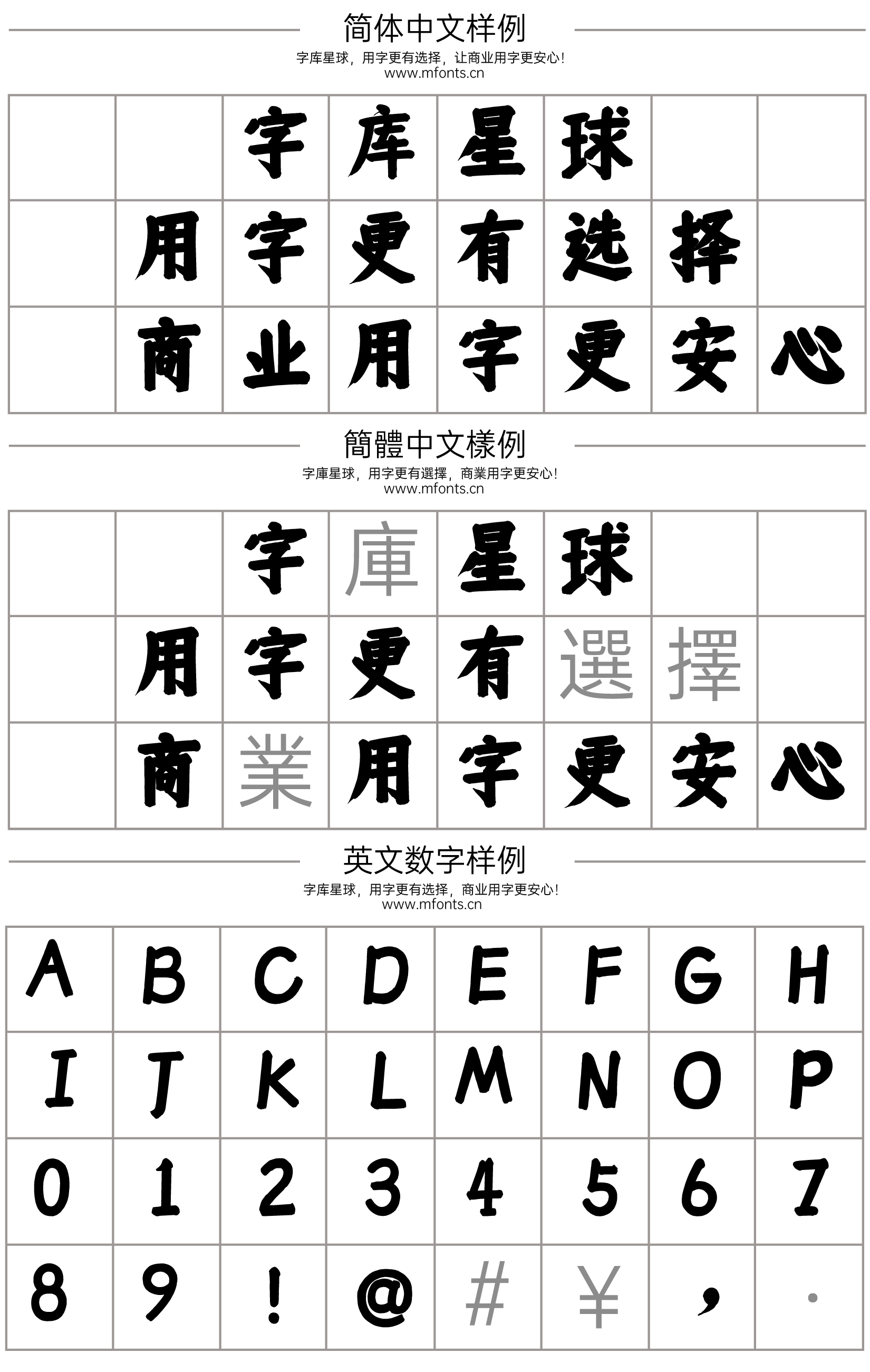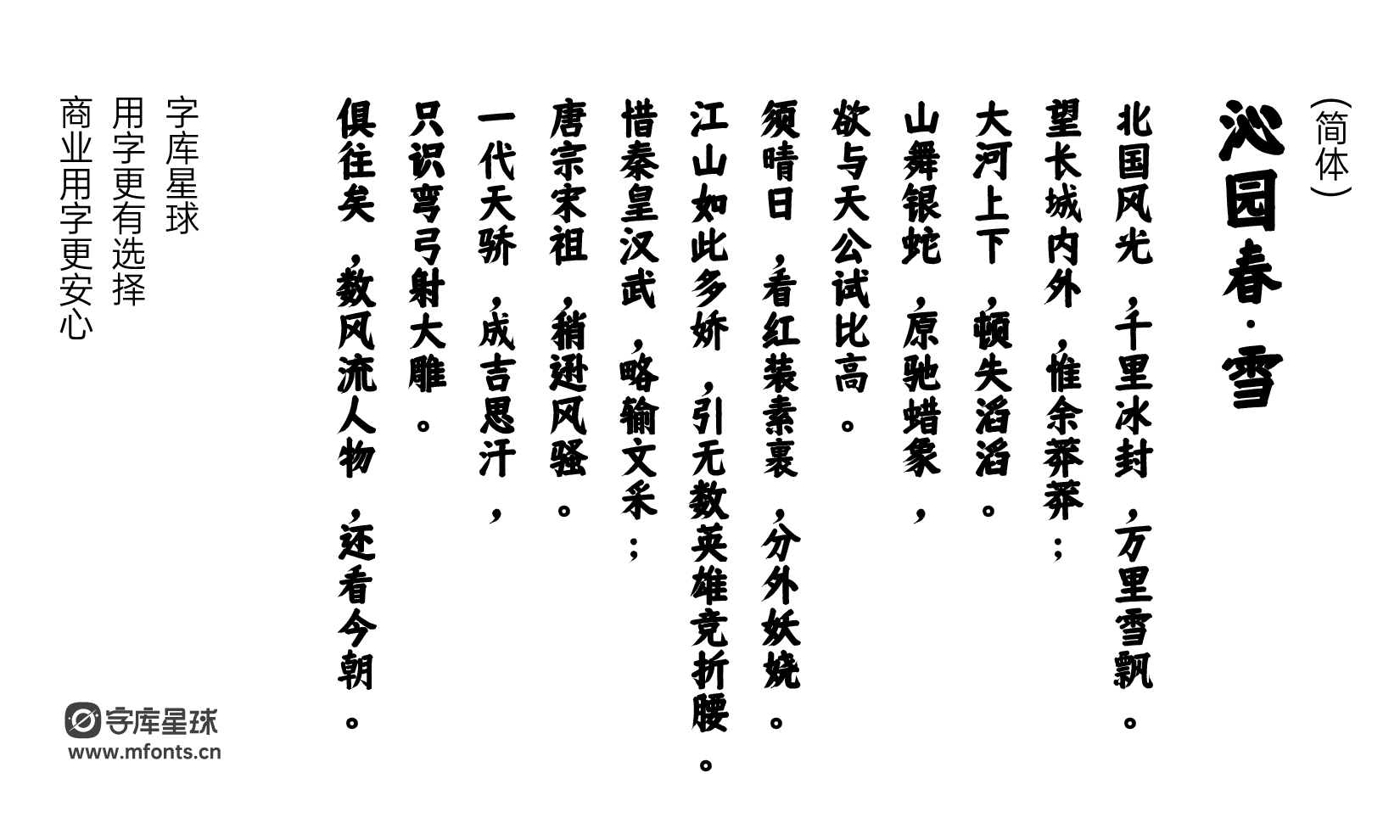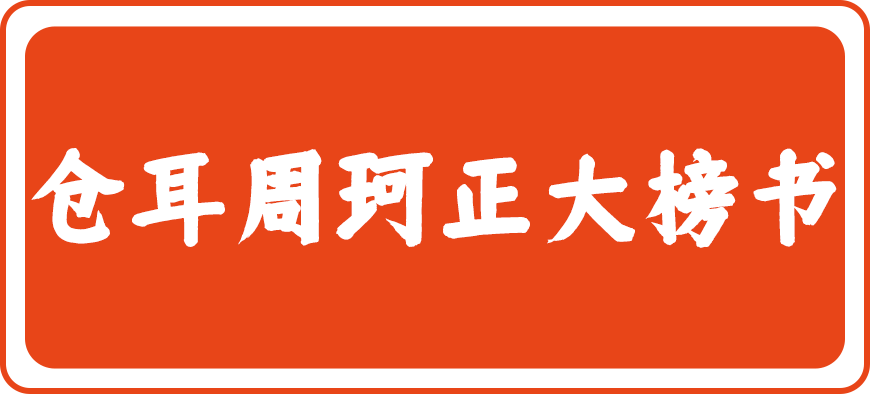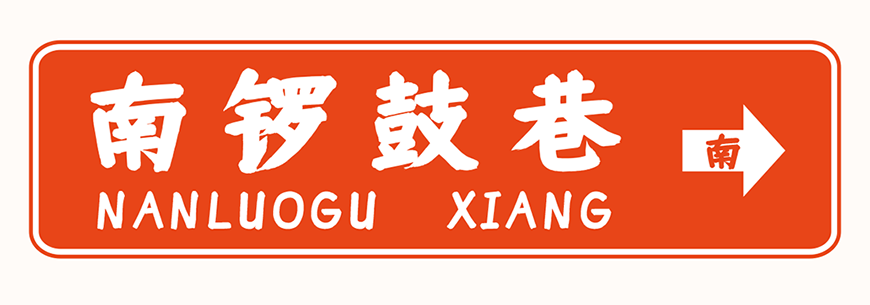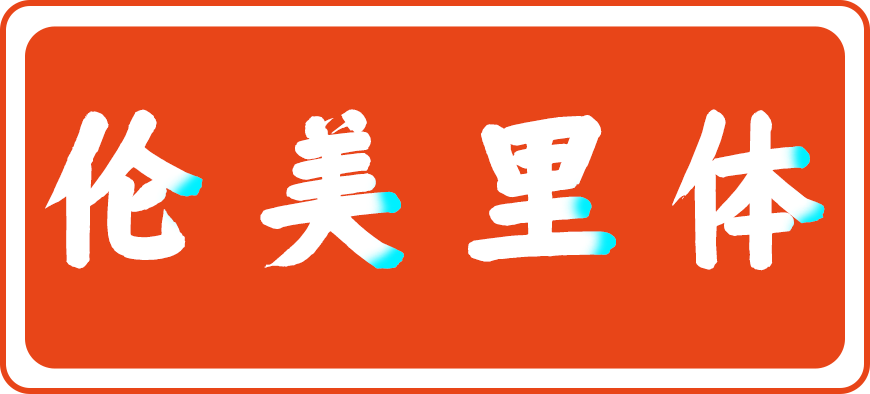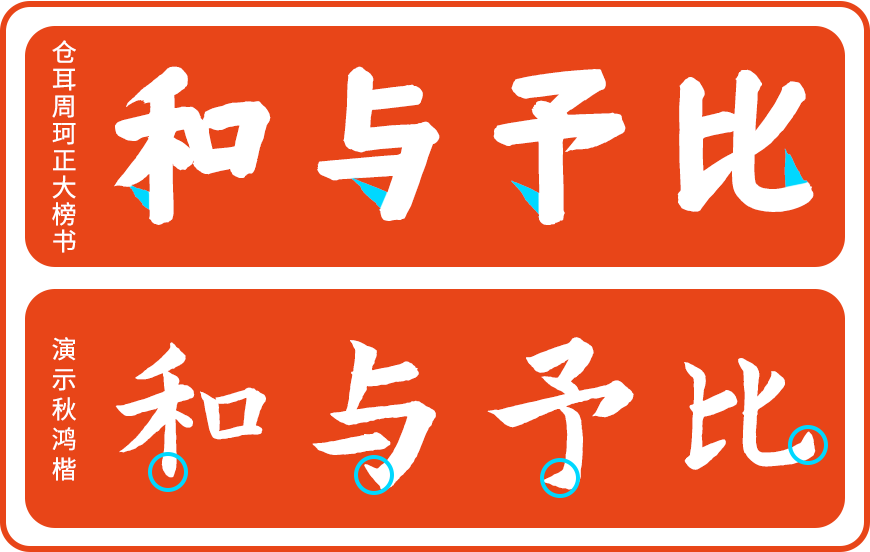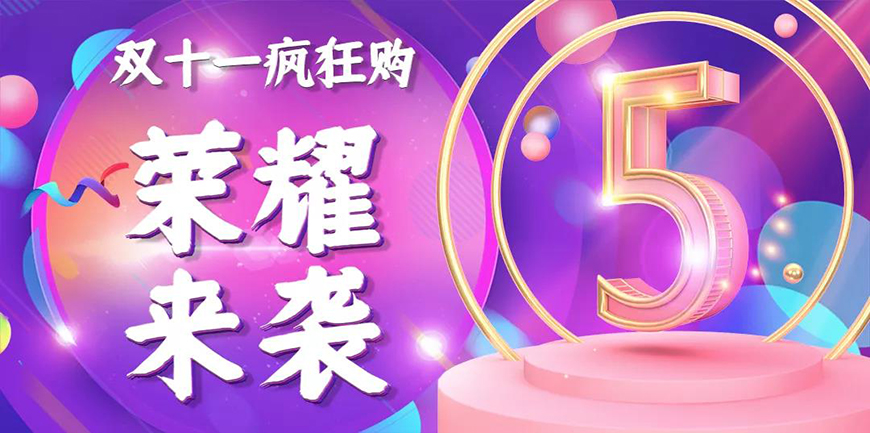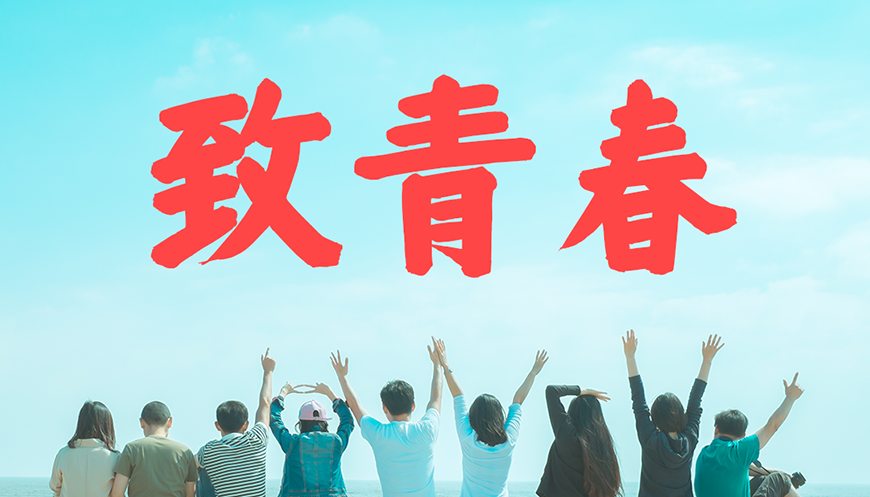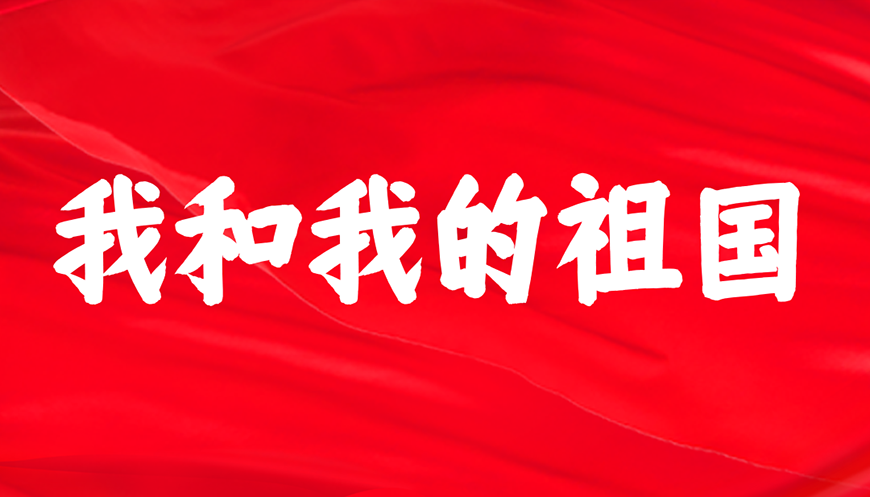
仓耳周珂正大榜书是仓耳字库推出的一款适应于任何用户全领域永久免费商用的书法艺术字体,字体笔触粗细适中,字形端正,具有很好的视觉感,适合应用于艺术设计、平面宣传设计、网页设计,书法字帖等领域。
仓耳周珂正大榜书笔画饱满圆润,在收笔处将笔锋恰到好处地停止,形成平滑的圆弧形,使得字体视觉上饱满有力。
另外,字体的钩笔画极其锋利,与圆润的收笔形成对比,使得笔画有干净利落之感。
该字体的整体笔画非常紧凑,很多笔画都粘连在一起,使得字体整体紧凑饱满,粗壮有力。
文章标题:仓耳周珂正大榜书